ロゴDAYS: 甲谷一のデザインと思考
手掛けたロゴデザインが100を越えるアートディレクター・甲谷一氏著書によるロゴデザインの夥しい思考や熟練されたテクニックのを作業プロセスと共にビジュアルにより解説した「ロゴDAYS: 甲谷一のデザインと思考」が誠文堂新光社から2018年10月1日に発売された。
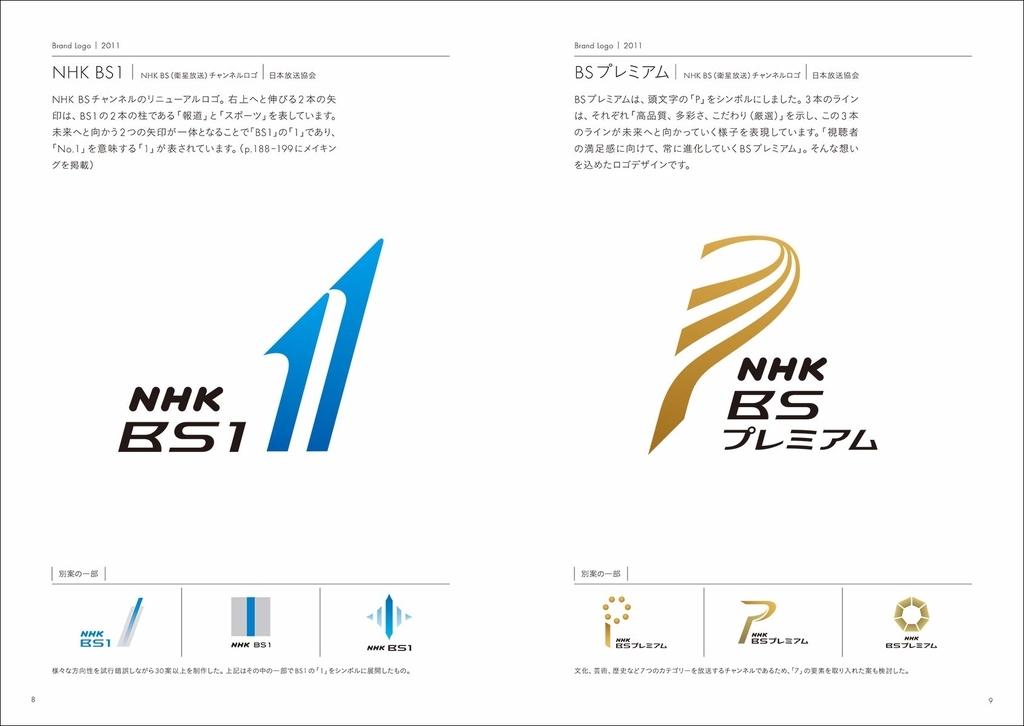
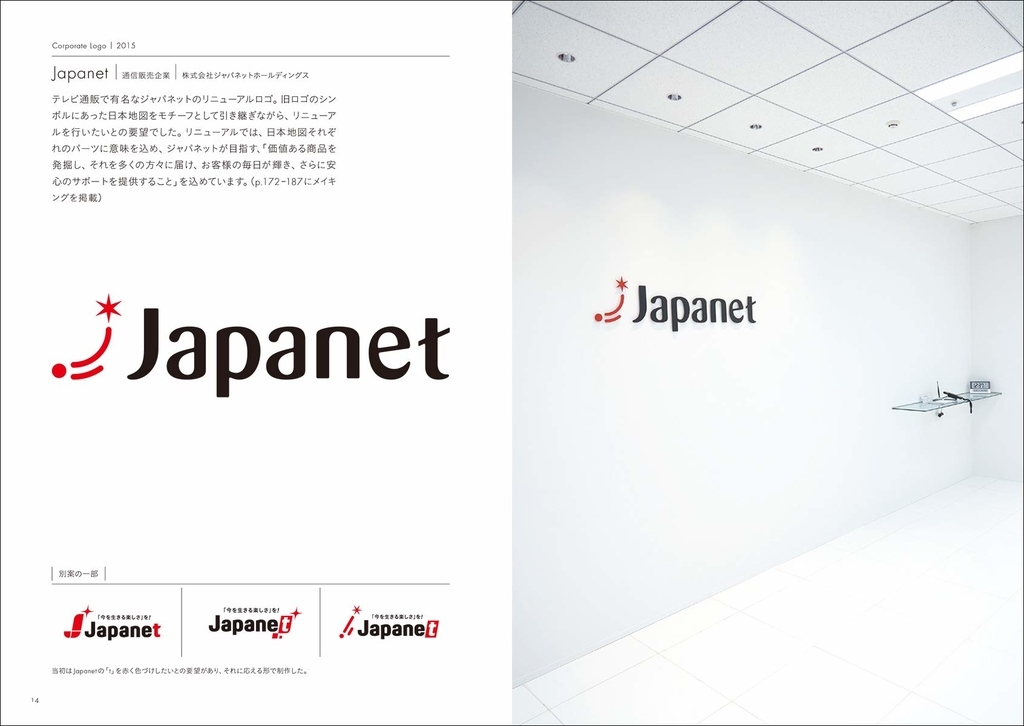
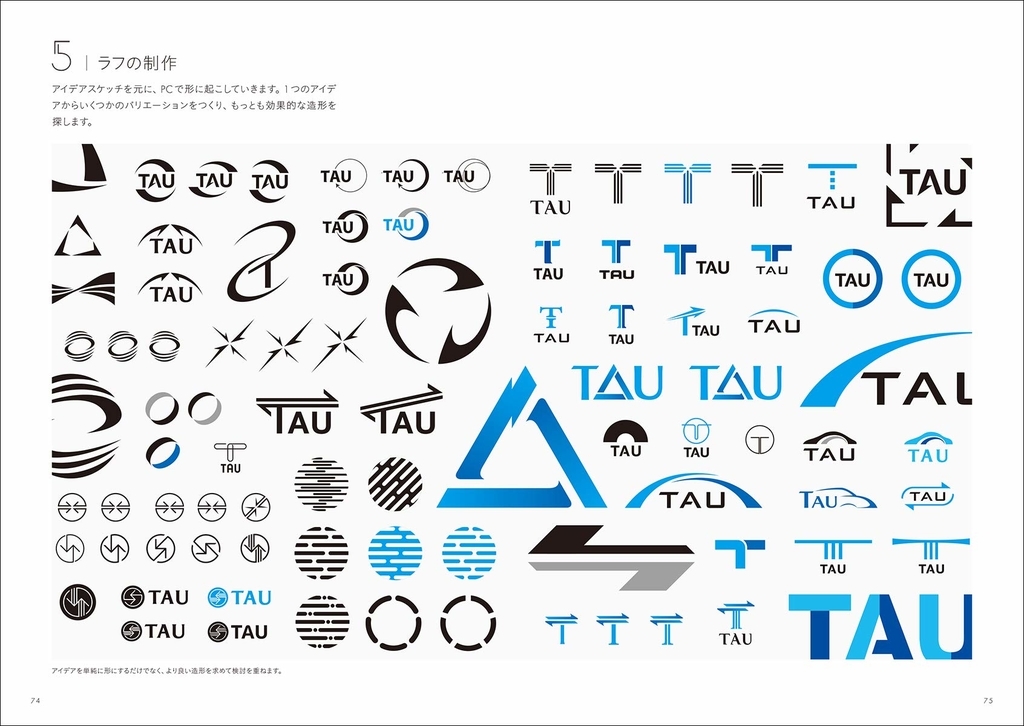
アートディレクター甲谷のロゴデザインの本質は、見た目の良いものを追求はするが、ロゴを機能させること。
それは企業や団体、店舗などが持つメッセージを突き詰めビジュアライズし、しっかり伝わるアイコンとなるものに仕上げることです。
このポリシーを貫き、今まで手がけたロゴデザインの数は優に100を越える。
言葉にすると硬いイメージがあるが、表現はとてもチャーミング。
抜けが良く爽やかな風が吹き抜けるとでも言いたくなるデザインが特徴。
ただ、甲谷の仕事はそれに反して、ロゴデザインに込める熱量は高く、仕上げまでのきめ細かいブラッシュアップには、濃密な時間が使われる。
同書では、甲谷の20年近いデザイン活動の中で培われた、ロゴデザインの夥しい思考や熟練されたテクニックの数々を、作業プロセスを追いかけながら、ふんだんなビジュアルによって解説します。
甲谷 一Profile●アートディレクター。1973年東京生まれ。2006年有限会社Happy and Happy設立。独自性の高いタイポグラフィを活かしたデザインを駆使し、ロゴやブックデザイン、広告等のデザイン全般を手掛ける。また、これまでに約40書体の欧文フォント制作を行っている。 著書に『たのしいロゴづくり』『きれいな欧文書体とデザイン』(ビー・エヌ・エヌ新社)、『ABC案のレイアウト』『デザインの組み方』(誠文堂新光社)『ハイグレード・デザインフォント』(エムディエヌコーポレーション)がある。
甲谷一氏著書「きれいな欧文書体とデザイン 名作書体の特色とロゴづくり 」
甲谷一氏著書「きれいな欧文書体とデザイン 名作書体の特色とロゴづくり」はビー・エヌ・エヌ新社から2010年2月22日に発売。
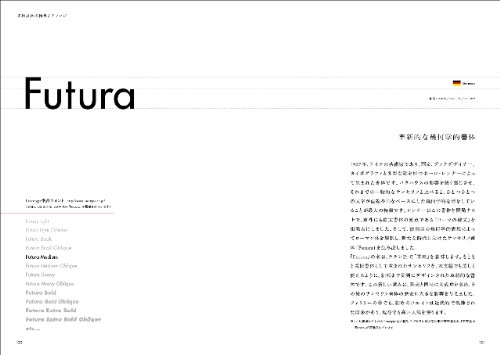
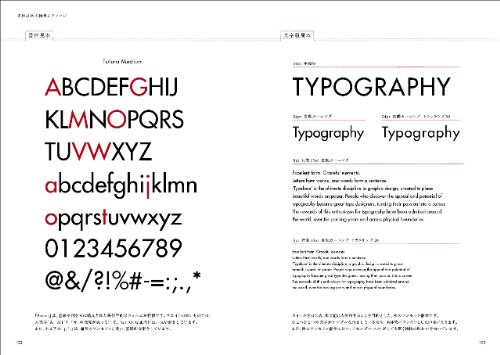
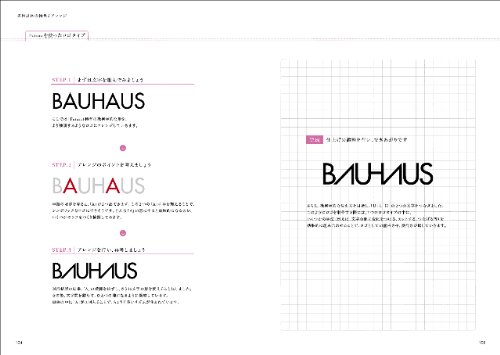
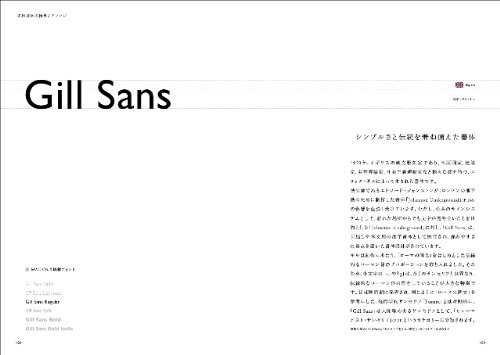
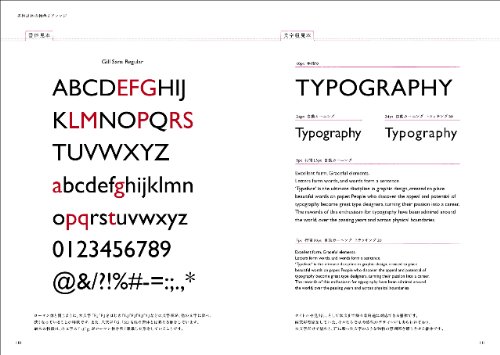
デザイナーなら知っておきたい定番・名作書体の歴史的背景はもちろんのこと、書体ごと、一文字ごとの“ デザイン的な特色"をビジュアル解説していることが本書の大きな特徴です。また日本では欧文書体を用いて、ロゴ制作をする機会が多いことにも着目し、欧文ロゴ制作の“ 実践的なノウハウ"をレクチャーしています。本書は、デザインの目的にあわせた書体選びに、すぐ役立てることができる、日本人デザイナーのための欧文書体入門の“ 決定版"です。
甲谷一氏著書「デザインの組み方 見てわかるレイアウトの新ルール」
甲谷一氏著書「デザインの組み方 見てわかるレイアウトの新ルール 単行本」は誠文堂新光社から2011年9月21日に発売。
基本のレイアウトや写真・イラストの扱い、配色など幅広いデザインのカテゴリーで、「現状のデザイン」と「さらに良いデザイン」を左右に並べ、「現状のデザイン」を、デザイン力のあるアートディレクター甲谷一氏のアドバイスによって、より質の高いデザインへと導き、ビフォア・アフターで比較解説する。その際、ポイントになるのは、「誰に何を伝えるためのデザインか?」。デザインする目的を把握し、見る人に的確に伝えるためには、どのような表現を選ぶべきか…その観点から丁寧に解説した、実践的な書籍を目指す。
<カテゴリー>
(1)基本レイアウト・構成
(2)写真・イラストの扱い
(3)文字
(4)配色
甲谷一氏著書「たのしいロゴづくり -文字の形からの着想と展開 」
甲谷一氏著書「たのしいロゴづくり -文字の形からの着想と展開 」はビー・エヌ・エヌ新社から2012年9月18日に発売。
本書では、欧文&和文ロゴの実践的な制作テクニックを、初心者の方にもわかりやすいように体系化して解説しています。文字の形の特徴から着想を得て、オリジナリティあふれる形を展開していく、著者のロゴ制作のプロセスは、ロゴ制作をはじめたい方、アイデアに悩んでいる方にとても役立つ内容です。著者が実際に手掛けたロゴの、ラフアイデア出しからブラッシュアップしていくまでの作業工程も掲載しています。
甲谷一氏著書「ABC案のレイアウト: 1テーマ×3案のデザインバリエーション」
甲谷一氏著書「ABC案のレイアウト: 1テーマ×3案のデザインバリエーション」は誠文堂新光社から2013年12月13日に発売。
同じ素材(写真、イラスト、テキスト)を使ってレイアウトをA案、B案、C案の3案の違うタイプに仕上げ、デザインのバリエーションの作り方を伝える。雑誌、ポスターなどのレイアウトを中心に、写真、文字、色など、訴求ポイントを変え3つのバリエーション案を作り、訴求ポイントを解説する。